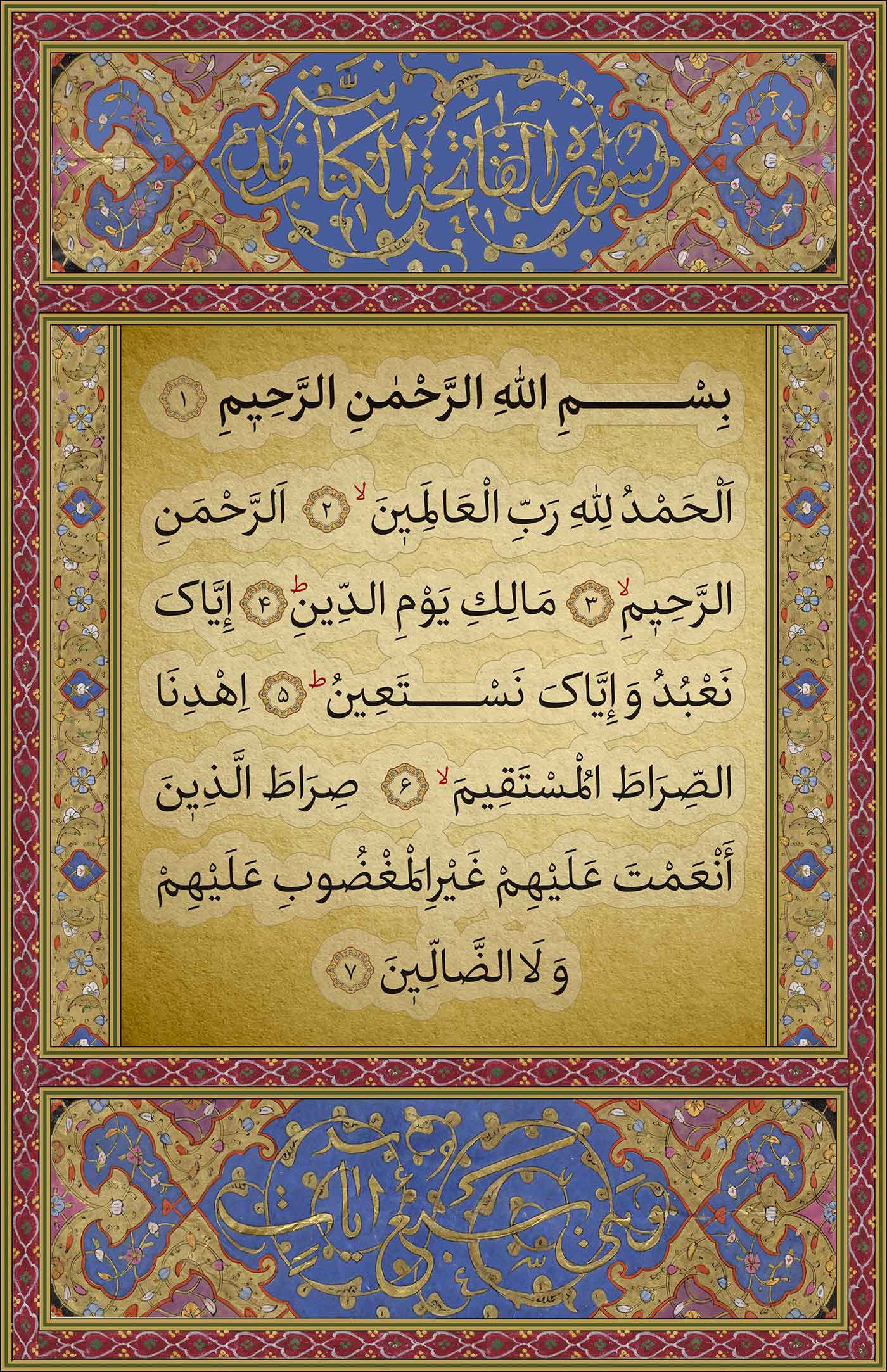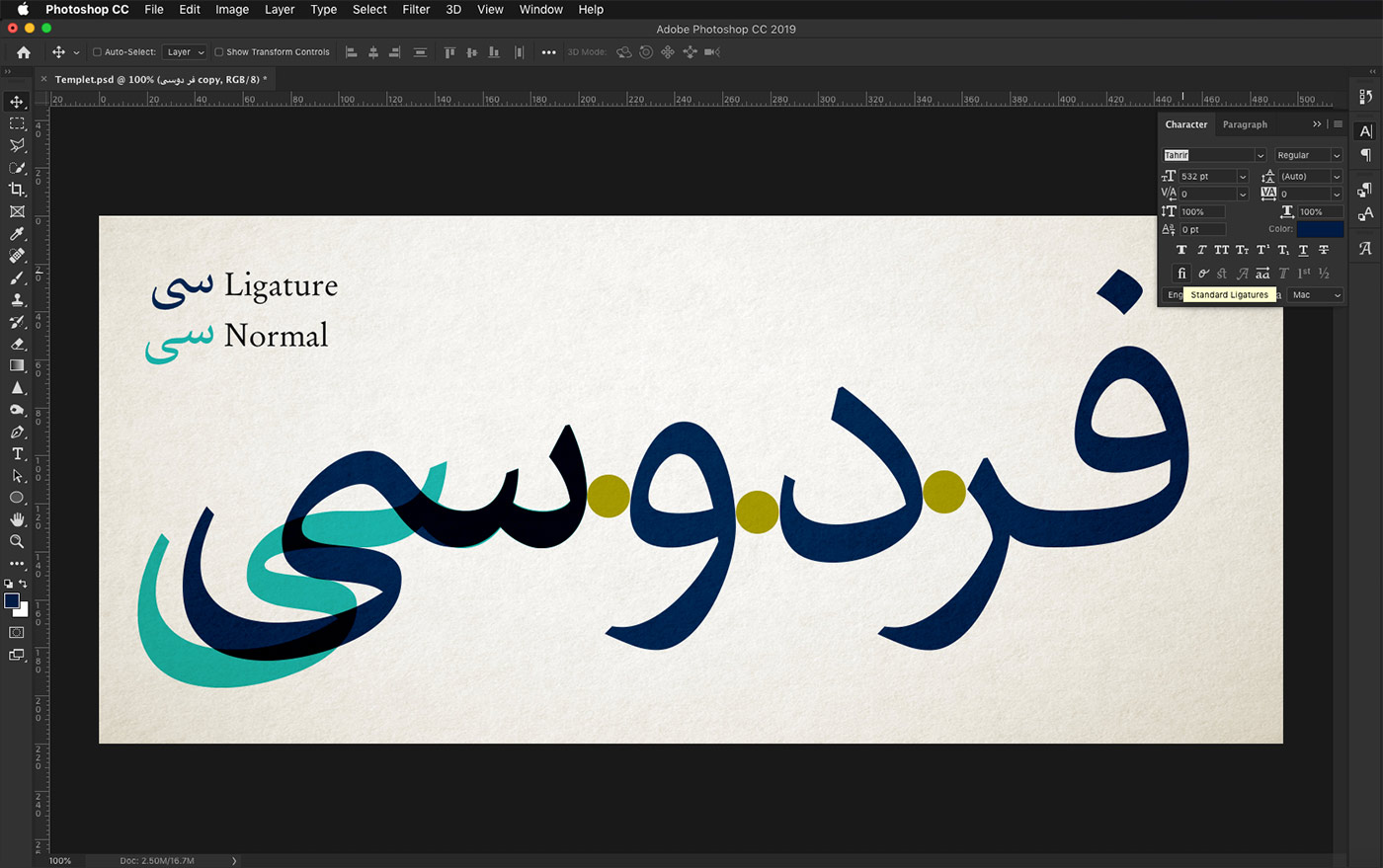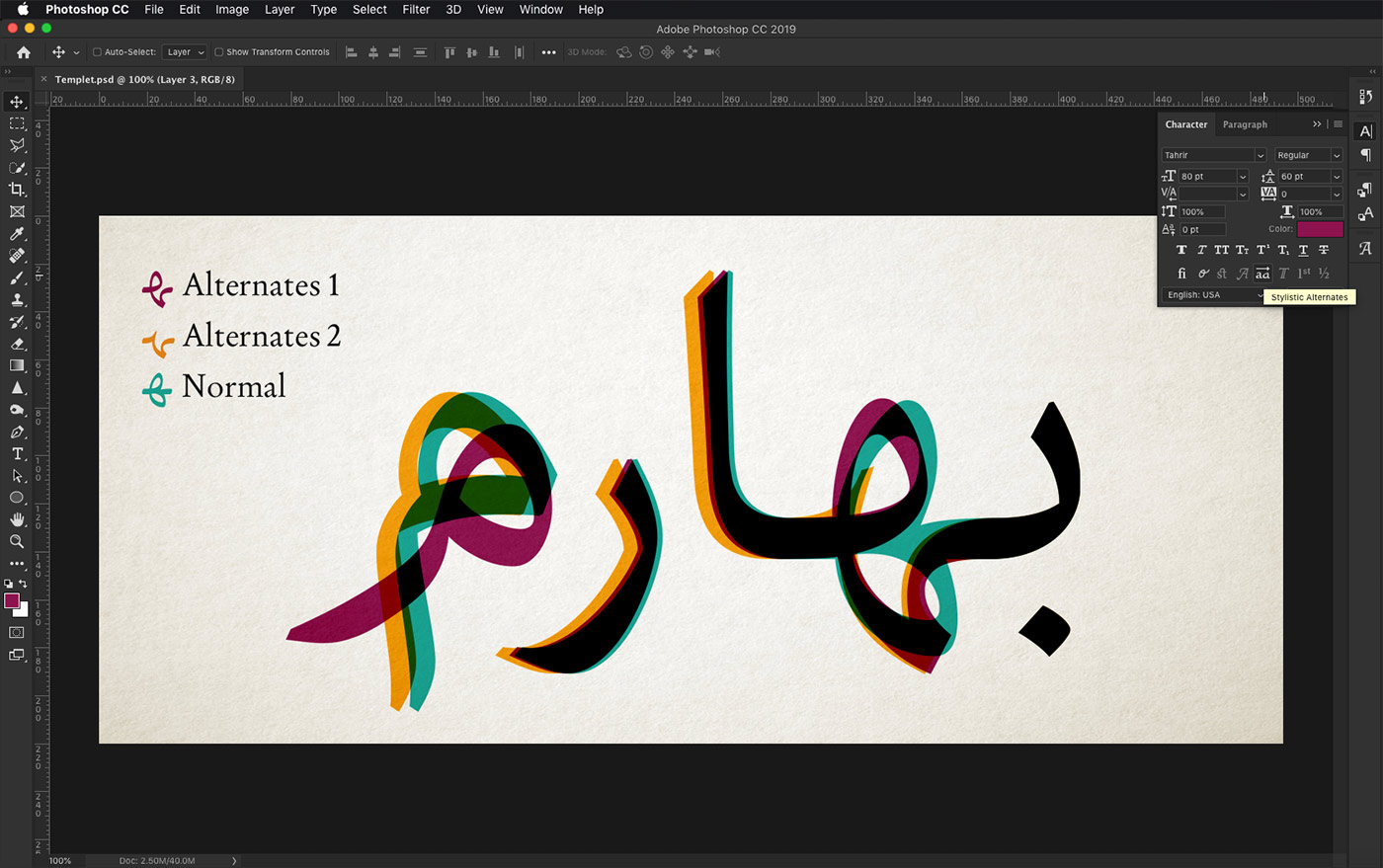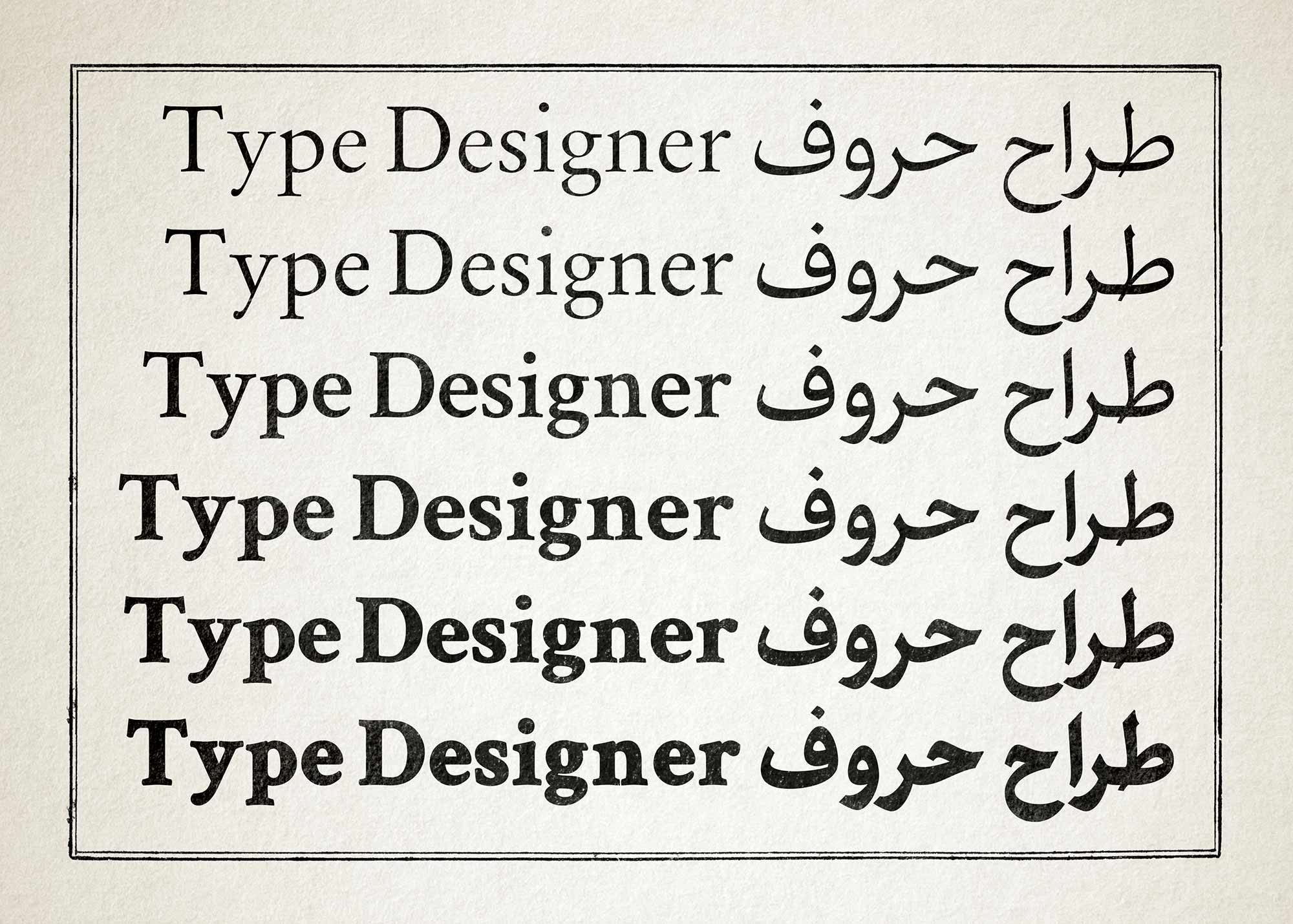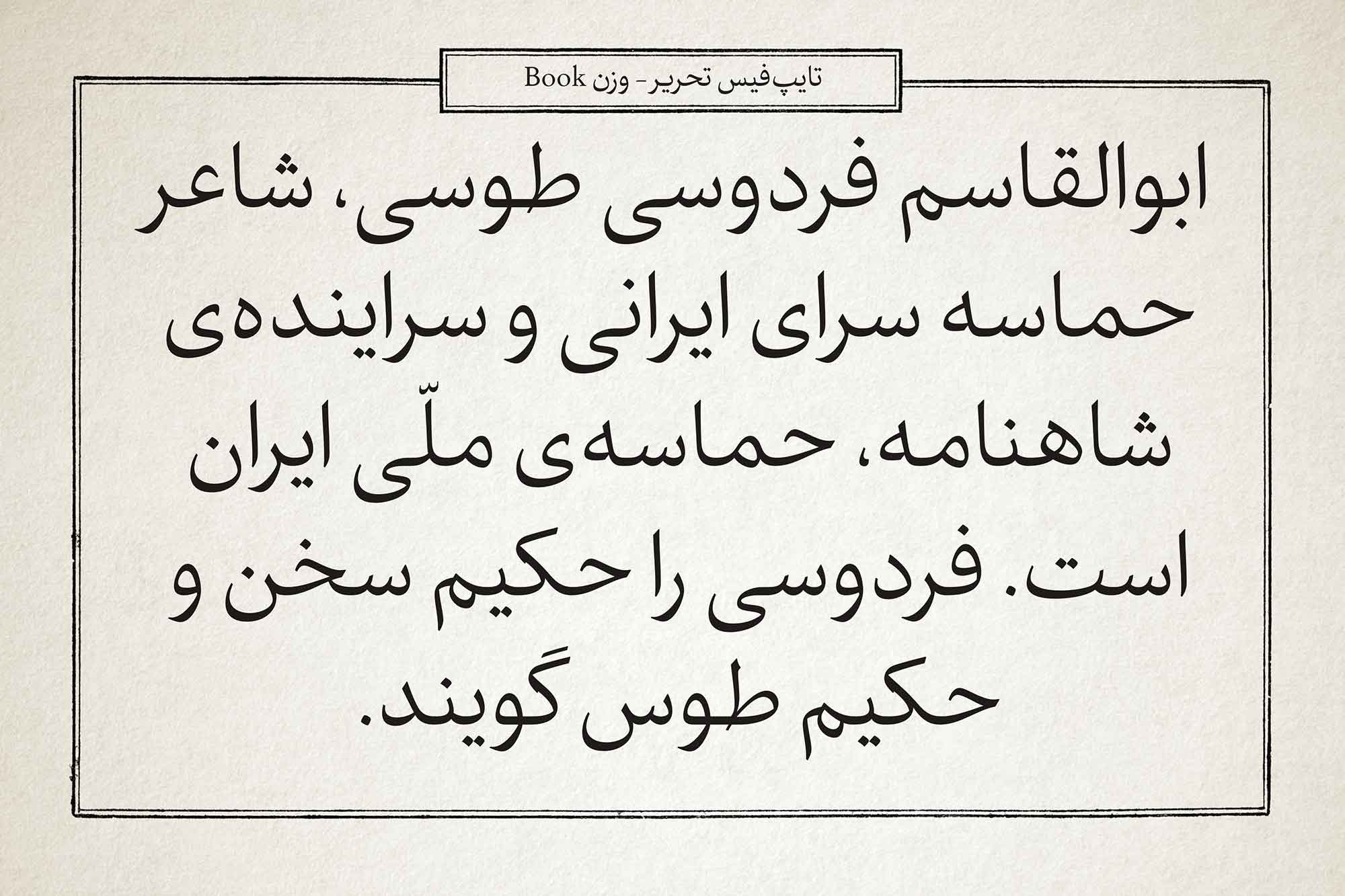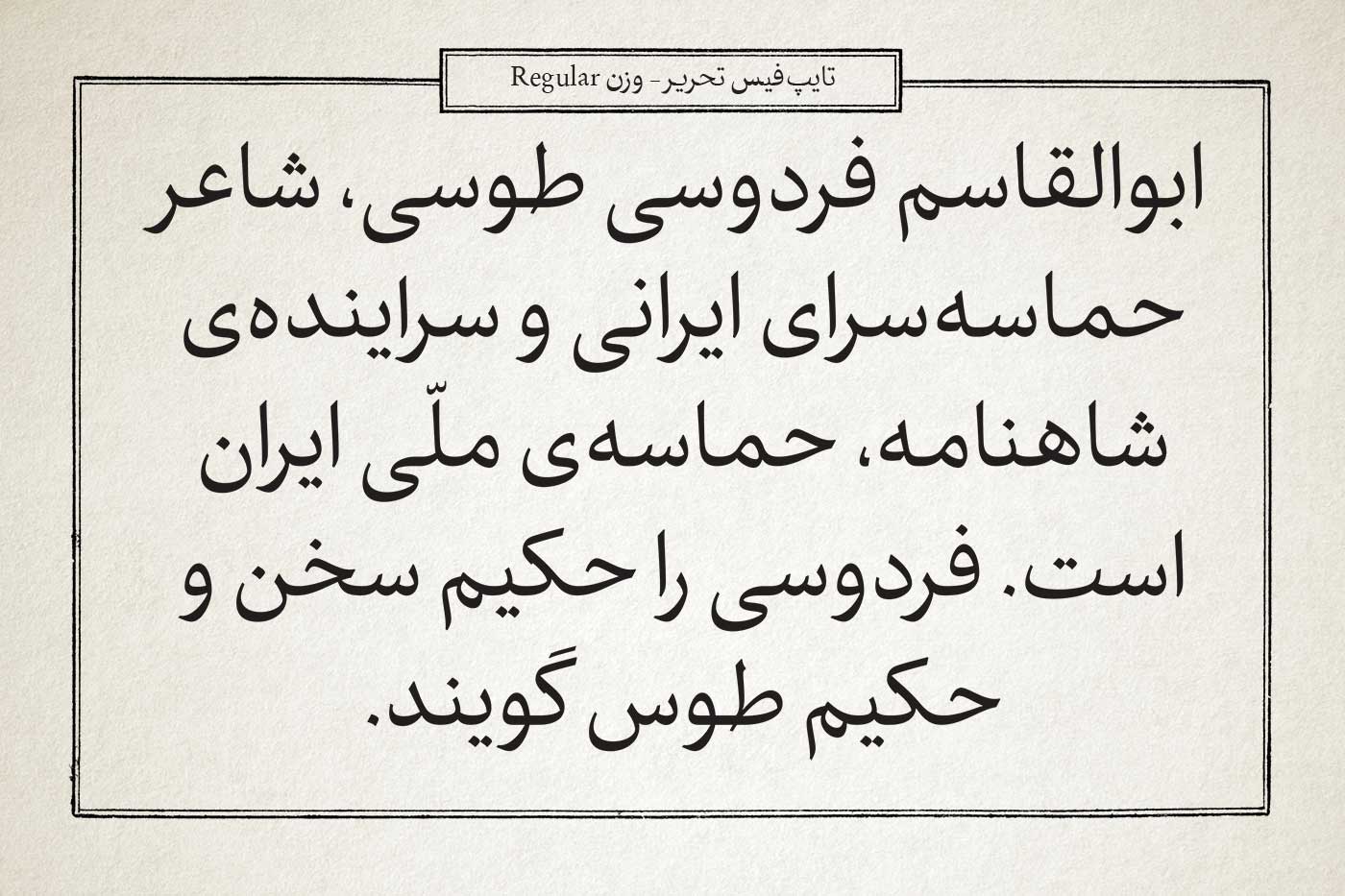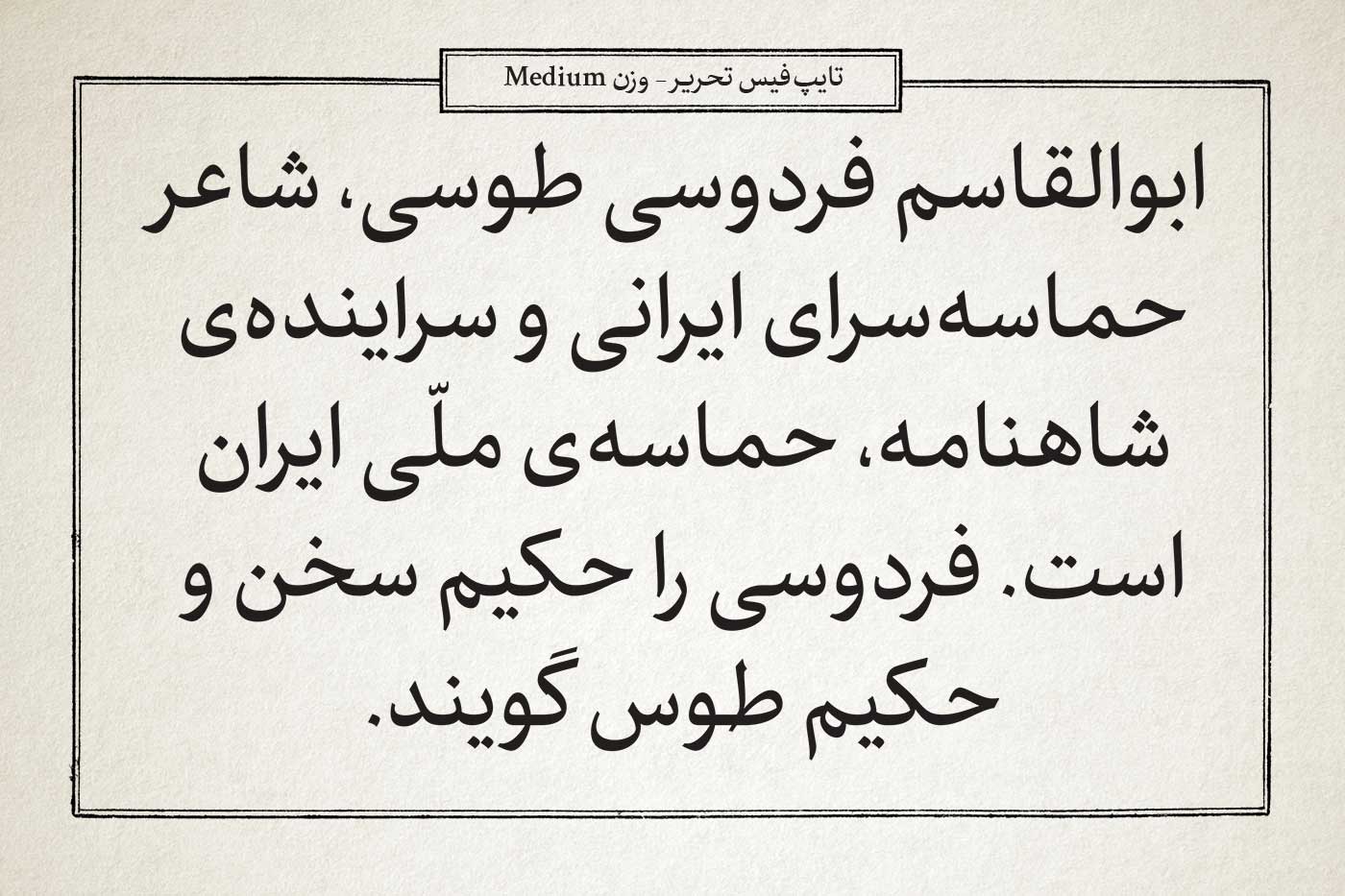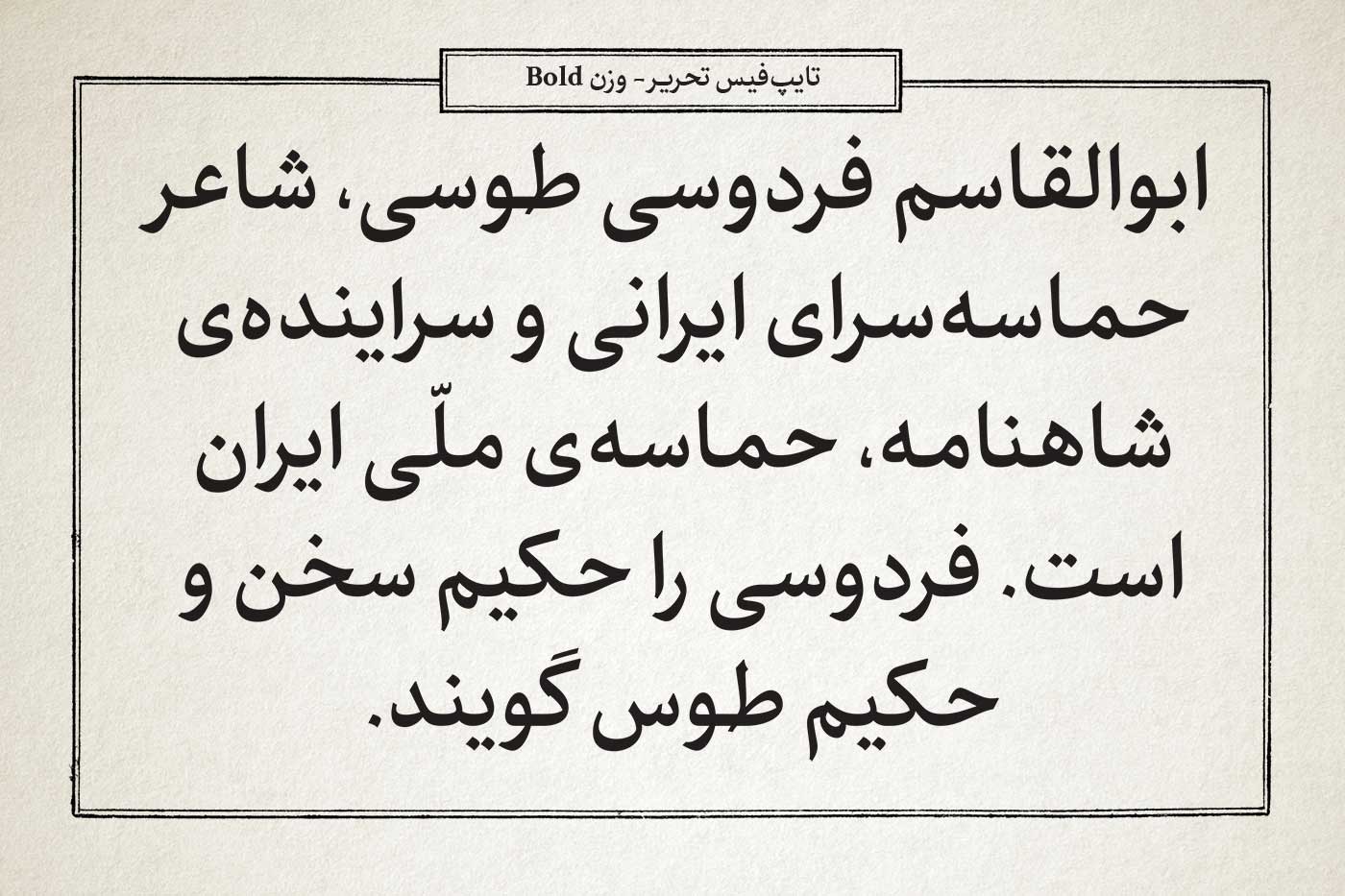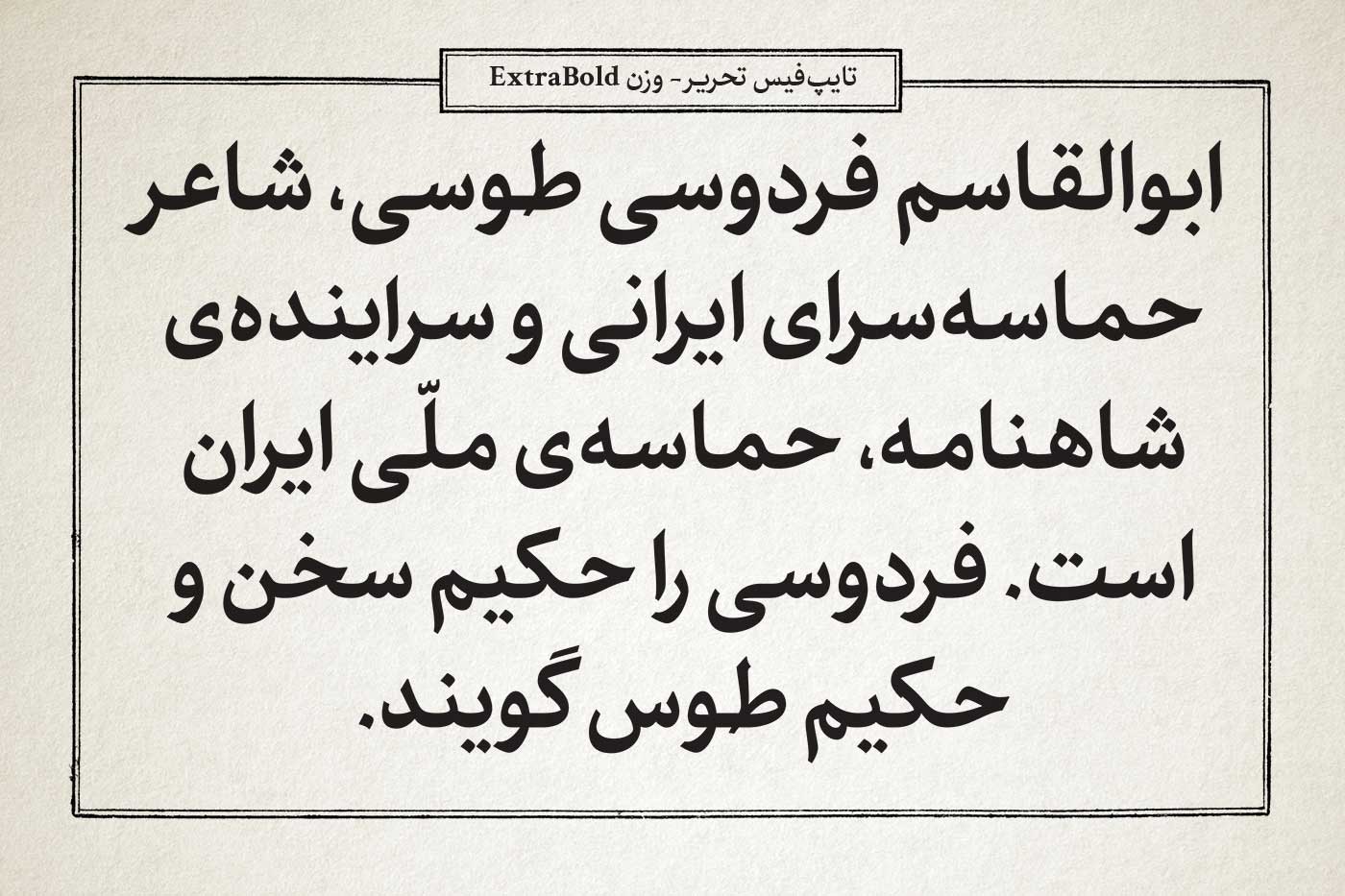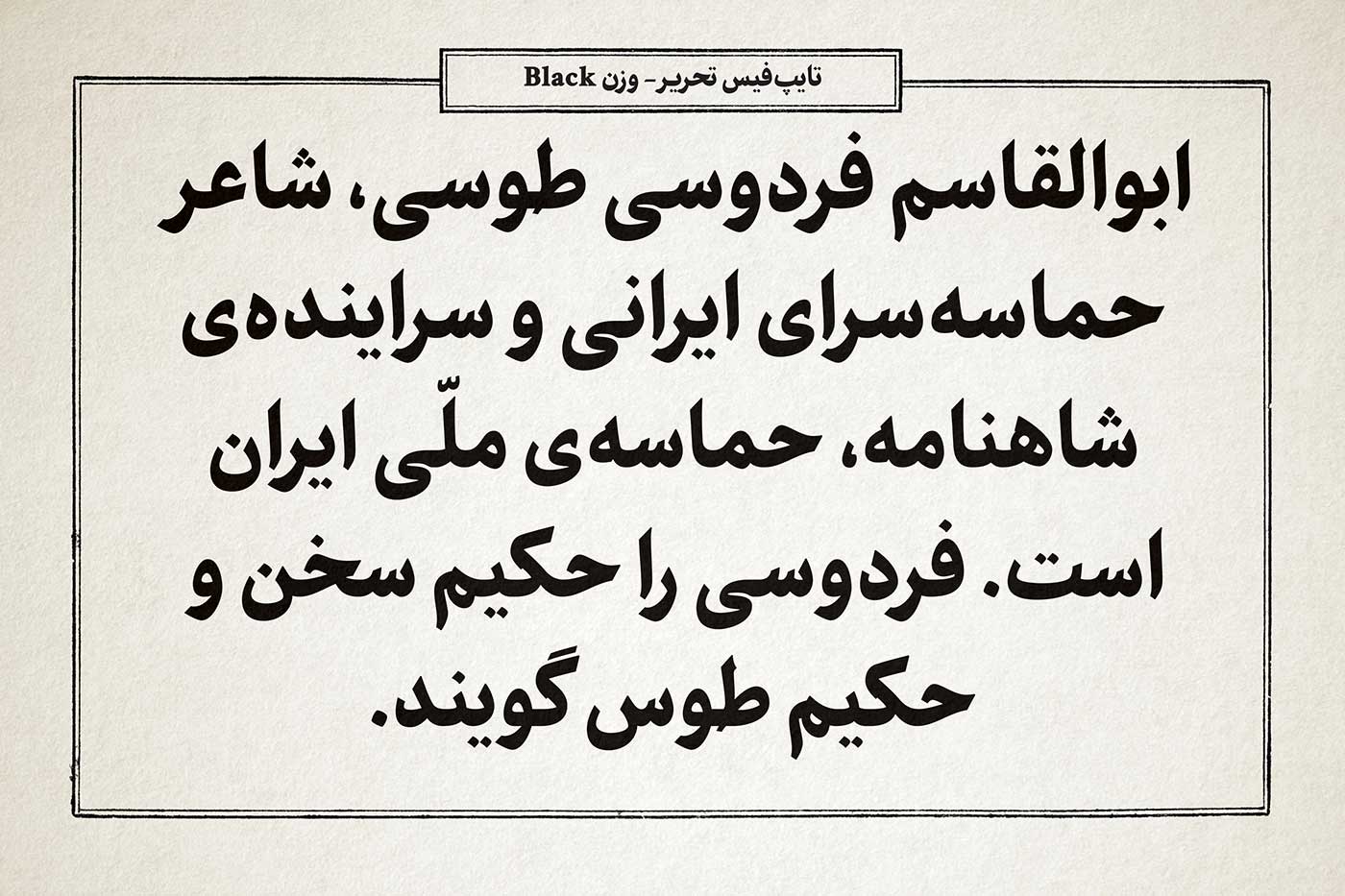
ویژگیهای اوپنتایپ در فونت تحریر
فونت تحریر در قالب اوپنتایپ و ویژگیهای این قالب طراحی و تولید شده است. تحریر با تنظیم فواصل و کرنینگهای متناسب با متن و بهرهمندی از حروف ترکیبی موجود در فونت تحریر تنوع فرمی بیشتری ایجاد کرده و به کمک آن، به متن جلوهای بسیار پویا بخشیده است، و به تولید طرحی کمک کرده است که الگوی کلی آن به ویژه در تنظیم روزنامهها بسیار مناسب است. فناوری دیجیتال با اجازه دادن به کاراکترهای گسترده و برخی از نمادهای اضافی، اعرابگذاری دقیق و همچنین با امکان استفاده از جایگزینهای متنی به فونت تحریر امکان داده طراحی متن را بهبود ببخشید و به این ترتیب نحوه تعامل و شیوه استفادهی طراح و تجربه کار با تایپفیس متن را ارتقا داده است.
کافیست در نرم افزارهای ادوبی از پنل تایپ کاراکتر Standard Ligatures را فعال کنید.
کافیست در نرم افزارهای ادوبی از پنل تایپکاراکتر Stylistic Alternates را فعال کنید.
خانوادهی تحریر
فونت تحریر در شش وزن نازک (Book) معمولی (Regular) میانه (Medium) تیره (Bold) بسیارتیره (ExtraBold) و سیاه (Black) موجود است. هر ۶ وزن فونت شامل گلیفهای لاتین هستند و در یک قلم منفرد میشود متن را در هر دو زبان لاتین و فارسی تنظیم کرد.
فونت تحریر مجموعه کاراکترهای اصلی لاتین را شامل میشود و از همه زبانهایی که از خط فارسی استفاده میکنند پشتیبانی میکند. اینها شامل عددی جدولی و متناسب عربی، فارسی و اردو و مجموعهای از اعداد جداول اروپایی (لاتین) است.